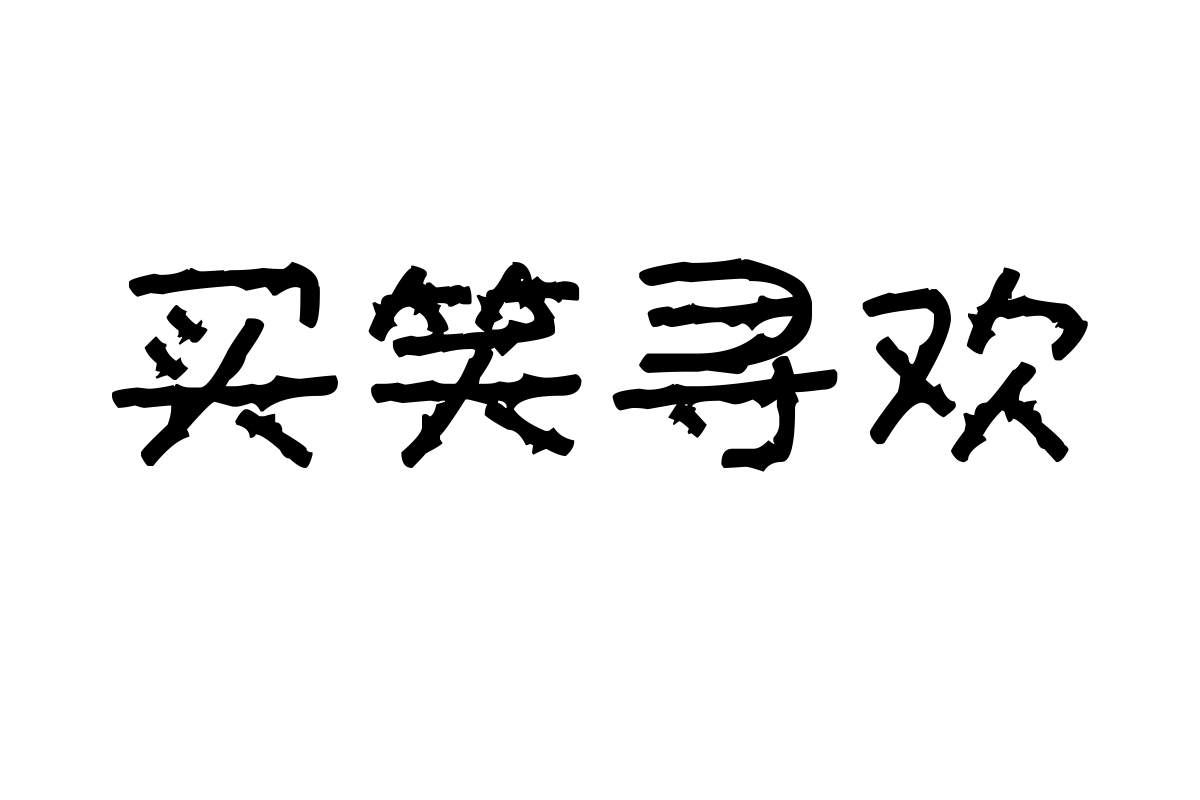
汉标胡杨枯木体字体是一种具有独特风格和特色的中文手写体。这种字体以其独特的笔画结构和流畅的书写线条而闻名,给人一种古朴、自然的感觉。
汉标胡杨枯木体字体的特点是笔画粗细变化较大,既有粗犷有力的部分,也有细腻柔和的部分。这种笔画的变化使得字体既有力量感,又不失灵动性。同时,这种字体的笔画结构也具有一定的规律性,使得整个字体看起来更加和谐统一。
此外,汉标胡杨枯木体字体还具有很高的辨识度。它的字形独特,与其他常见的中文手写体相比,有着明显的区别。这使得它在书法作品和设计作品中具有很高的审美价值。
总的来说,汉标胡杨枯木体字体是一种非常独特且具有艺术价值的中文手写体。它以其独特的笔画结构和流畅的书写线条,给人以古朴、自然的感觉,是书法爱好者和设计师们不可多得的选择。